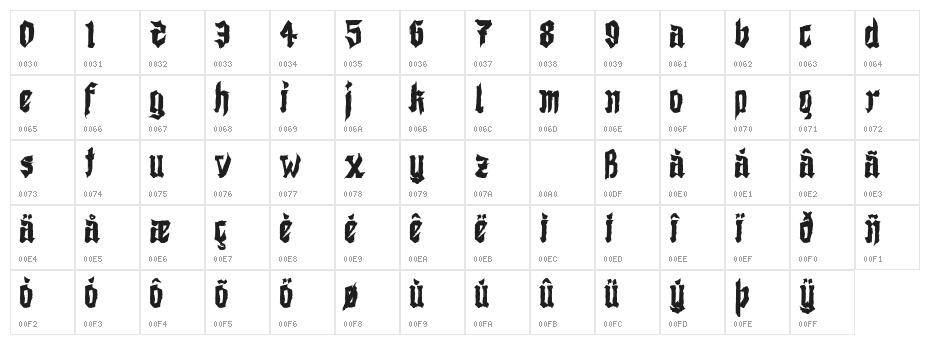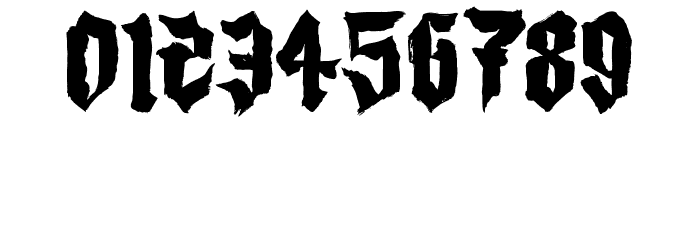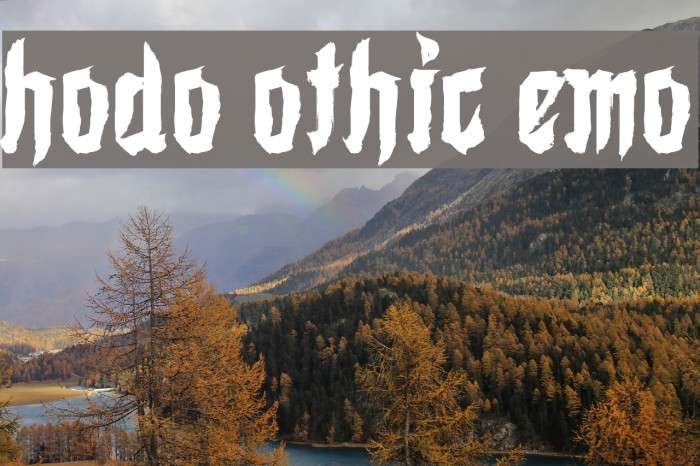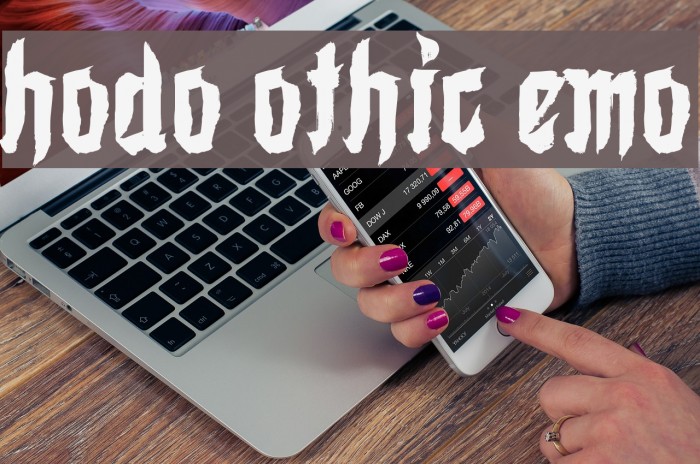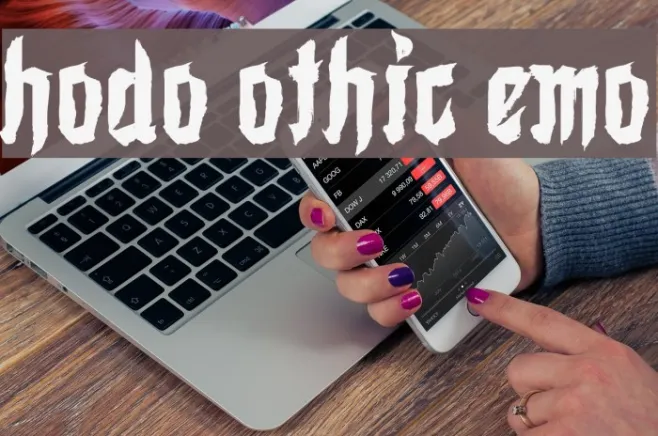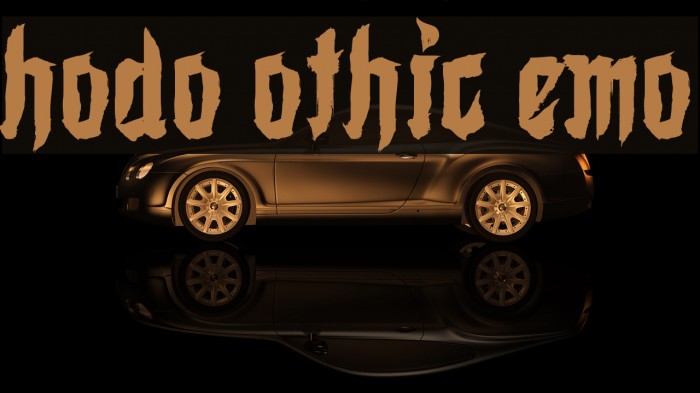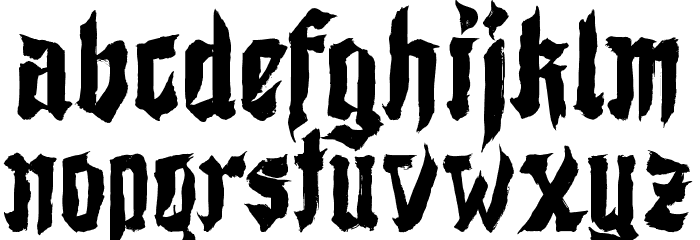
Shodo Gothic Demo Font
✎ Calligraphic
| Proyectos propuestos | Perfect for use in posters, book covers, branding for historical events, or any project needing a dramatic and artistic touch. |